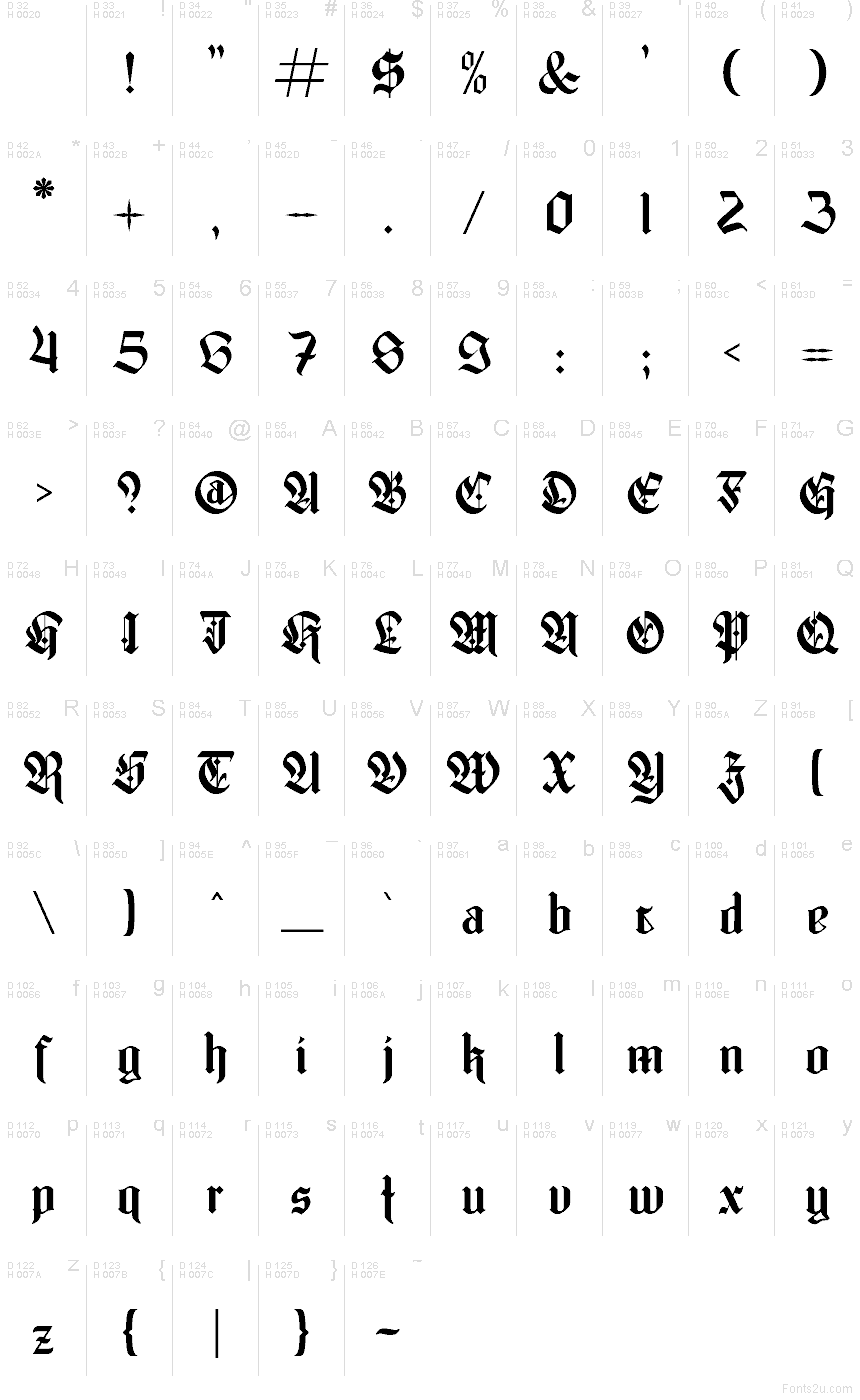
Machester est une police gothique médiévale gratuite qui capture le rythme cérémoniel et tranchant des lettrages blackletter. Avec ses arcs brisés, ses traits fendus et ses terminaisons en crochet, elle confère au design un aspect ciselé, une voix historique qui évoque l'héraldique plutôt qu'une simple décoration.
Elle est idéale pour les étiquettes de bières, les couvertures de romans fantastiques, les logos de groupes, les affiches d'événements et les menus de pubs où une touche historique forte est nécessaire sans tomber dans la caricature. Utilisez-la pour des titres courts, des cartes de titres ou des lettrines lorsque vous souhaitez que sa texture dense et sa silhouette anguleuse fassent tout le travail.